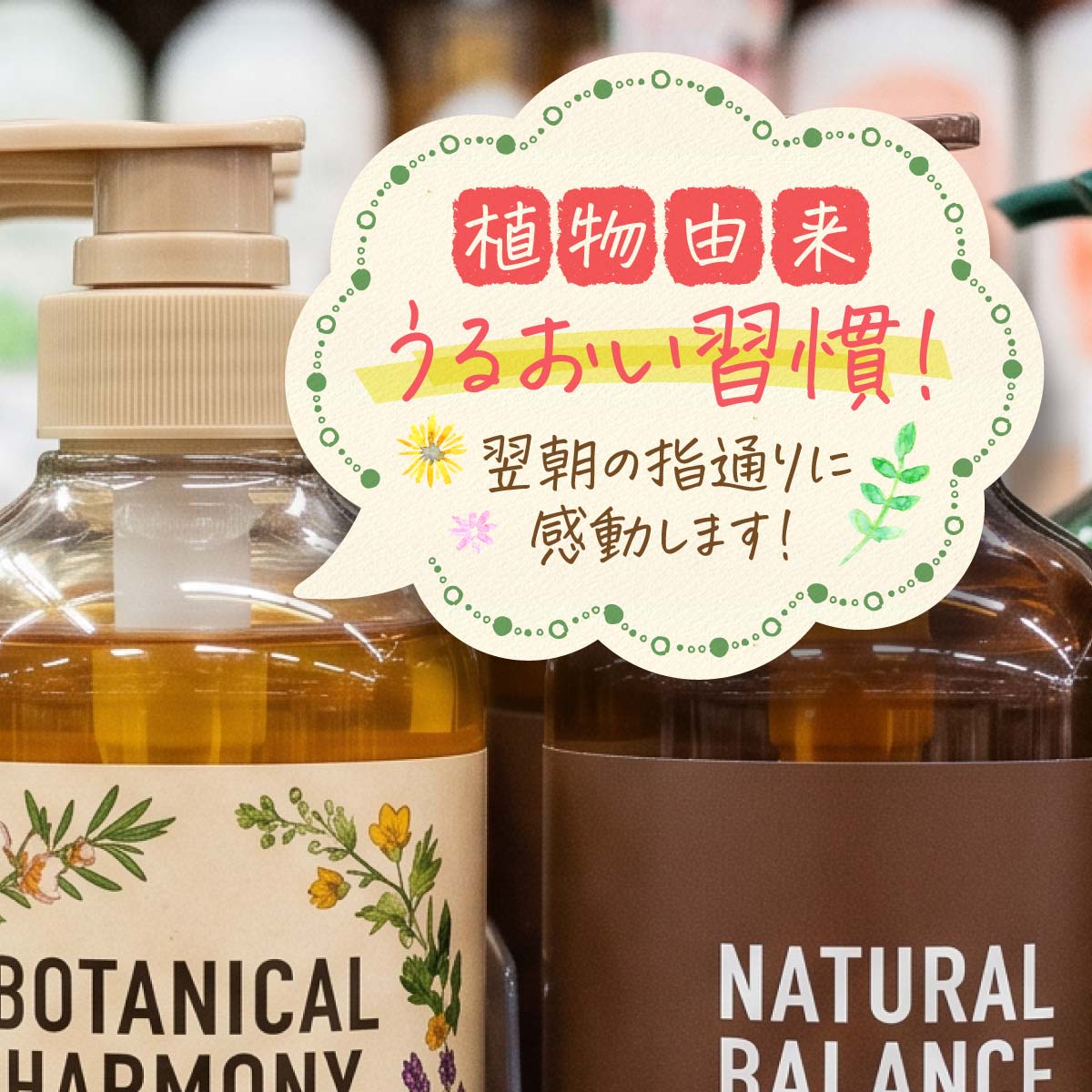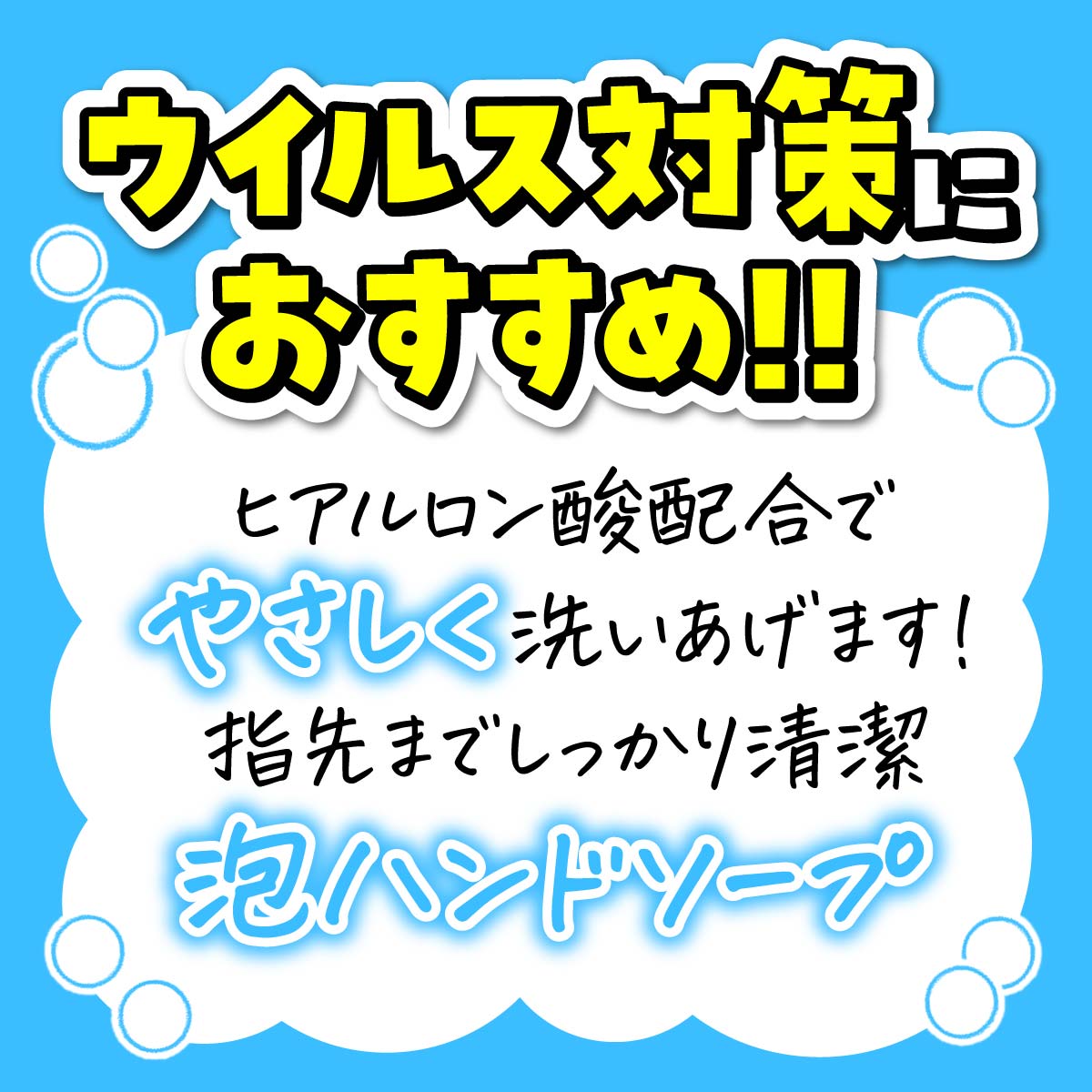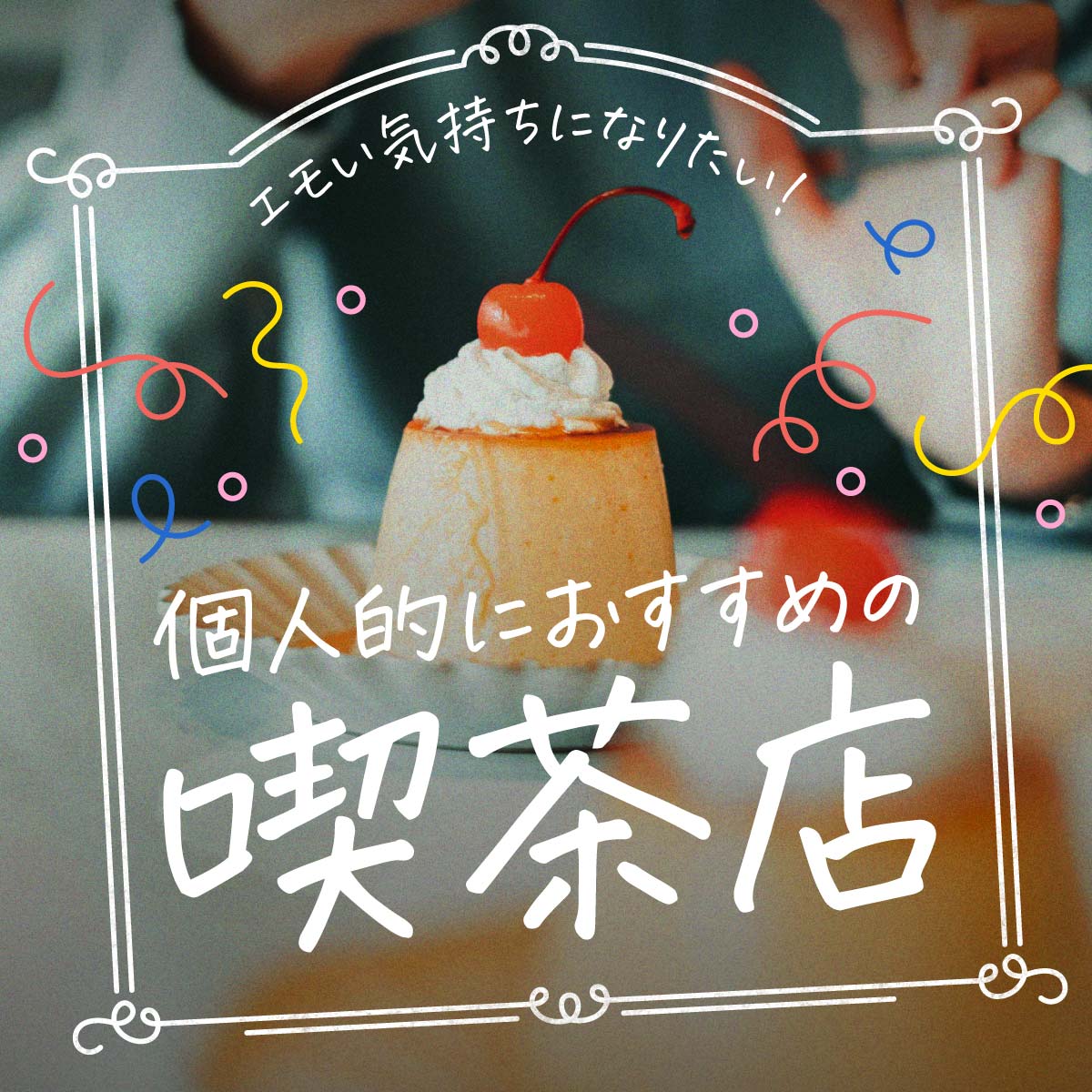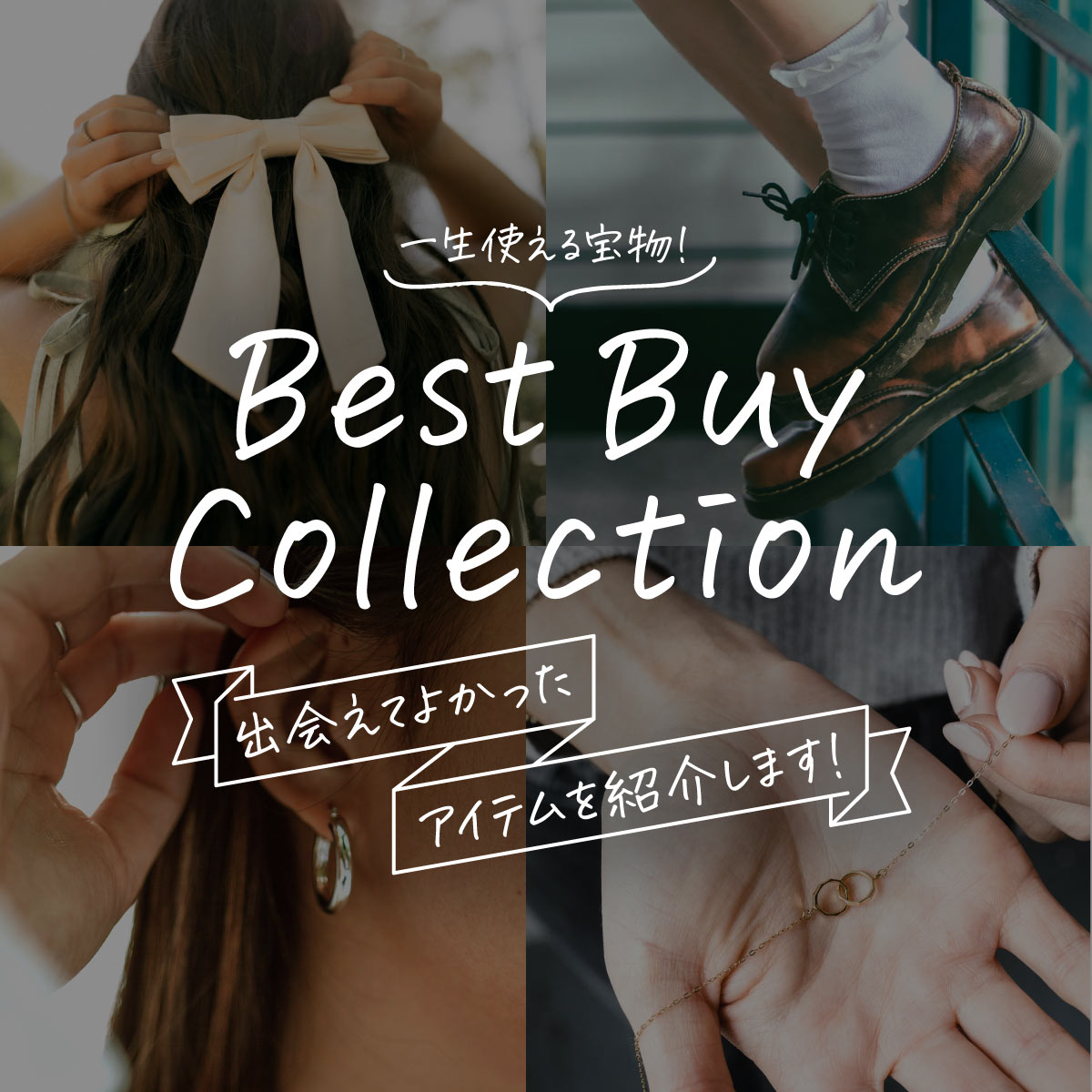
手書きフォント 鈴木メモ「花とちょうちょ」
「パンダベーカリー」「空とひこうき」「波とかもめ」が大ヒット中のフォントブランド 【鈴木メモ】が贈るSNSで話題沸騰中の大注目フォントです。
「花とちょうちょ」は、ペンで書いた手書き文字がベースのフォント。右上りの勢いと何より可愛らしいリアル手書き感が特徴です。手書き感が欲しいメニューやPOP、インスタ映えする写真のアクセントに、おしゃれ感溢れるYouTube動画、ディスプレイ広告のバナー、絵本などの書籍のほか、柔軟なライセンスで印刷からWebコンテンツ、ゲーム・アプリ、映像まで幅広く活用できます。
鈴木メモ
花とちょうちょ
作品づくりが楽しくなる、おすすめフォント!
ペンで右上がりに書いた手書き文字がベースのリアル系手書きフォント
手書きフォント 花とちょうちょ コンセプト
花とちょうちょの文字サンプル
手書きフォント 花とちょうちょ 文字見本 手書きフォント 花とちょうちょ 組み見本
花とちょうちょのひみつ
その1.横にさらさらと流れるように読める仮名のデザイン
ひらがな・カタカナ・アルファベットなどは、最後に傾けて確認しハパバのように濁音半濁音があるものは少し形を変えています。
手書きフォント 花とちょうちょ ひらがなのデザイン 手書きフォント 花とちょうちょ カタカナのデザイン
その2.長文でも読みやすい漢字のデザイン
漢字は、外形は台形を意識した右上がりに、右下には長く払わず横の流れを強調するように流すか跳ね上げる。
画数の少ない文字ほど動きを出して、画数の多い文字は傾きを控えて長文を読みやすく。
手書きフォント 花とちょうちょ 漢字のデザイン
その3.アルファベット・カタカナ・ひらがなはプロポーショナル
見出しなどで漢字が詰まって気になるときは、Adobe Illustratorなどでカーニングをオプティカルにしてから、トラッキング数値を広めにして使うのがおすすめです。
手書きフォント 花とちょうちょ 漢字のデザイン
こんな用途におすすめ
カフェ・レストランなど、メニューやPOPなど手作り&リアル手書き感を出したいジャンルに
手書きフォント 花とちょうちょ メニューでの使用1 手書きフォント 花とちょうちょ メニューでの使用2
コスメ・手作り・文具など、ちょっと話言葉などを添えたいときなどに
手書きフォント 花とちょうちょ コスメ・手作り・文具での使用1 手書きフォント 花とちょうちょ コスメ・手作り・文具での使用2 手書きフォント 花とちょうちょ コスメ・手作り・文具での使用3
その他の使用例
手書きフォント 花とちょうちょ 使用例01 手書きフォント 花とちょうちょ 使用例02
花とちょうちょの仕様
漢字もたっぷり、約6,700字入り
第一水準、第二水準、IBM拡張漢字を収録。日常で使う文字はほぼカバー出来ます。
第二水準漢字の苺・珈琲・贅沢など使用頻度が高いものも空白にならずに表示できます。
手書きフォント 花とちょうちょ 漢字約6,700字
新スタンダードのJIS2004字形で収録しています
デザイン書体ではまだちょっと珍しい、JIS2004字形を採用しています。収録は第2水準漢字まで。
手書きフォント 花とちょうちょ JIS2004字形
縦書きにも対応しています
手書きフォント 花とちょうちょ 縦書き
令和合字(Unicode 32FF)、é(アクセント付きのe)なども入っています
手書きフォント 花とちょうちょ 令和合字 é
手書きフォント 花とちょうちょ JIS2004字形